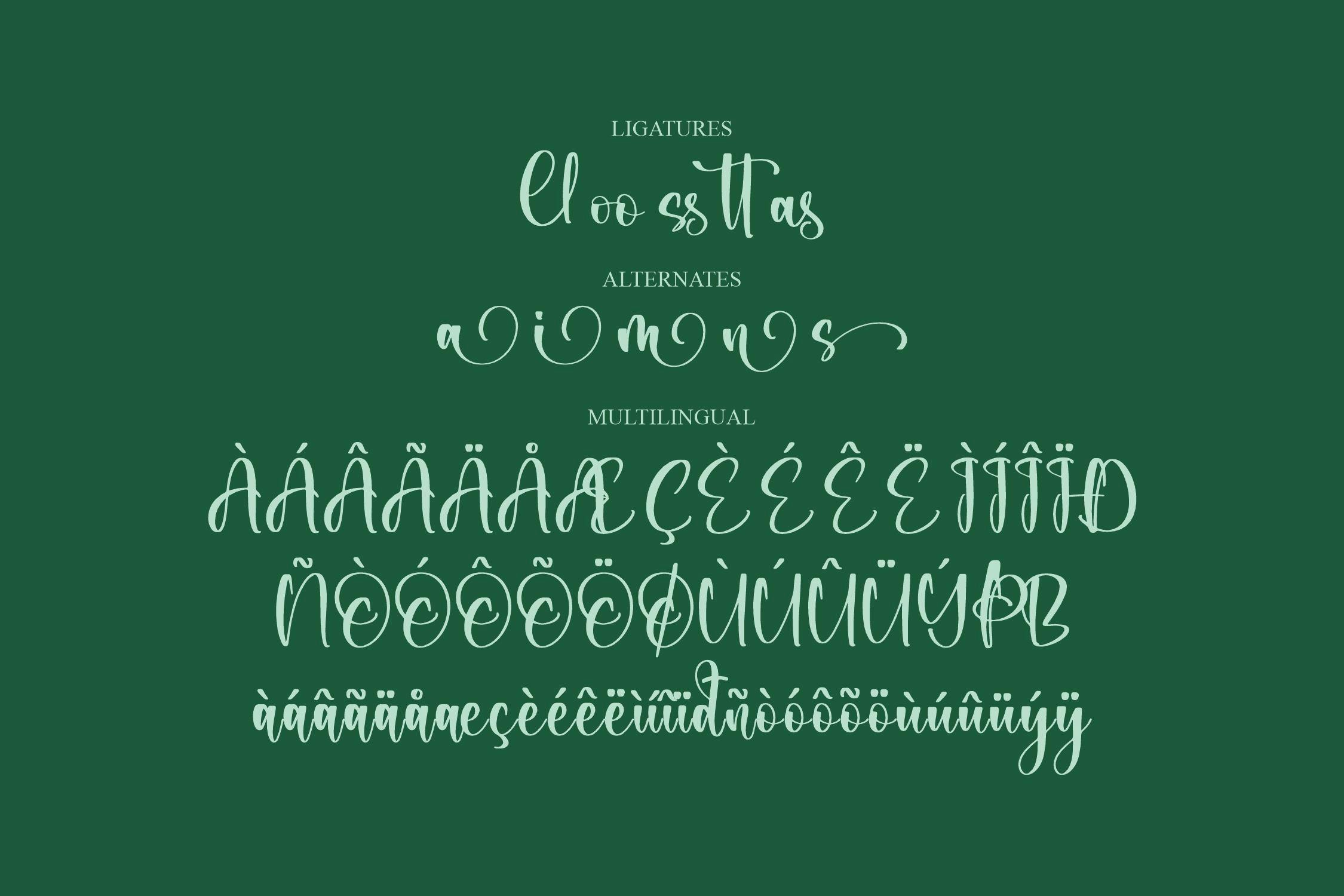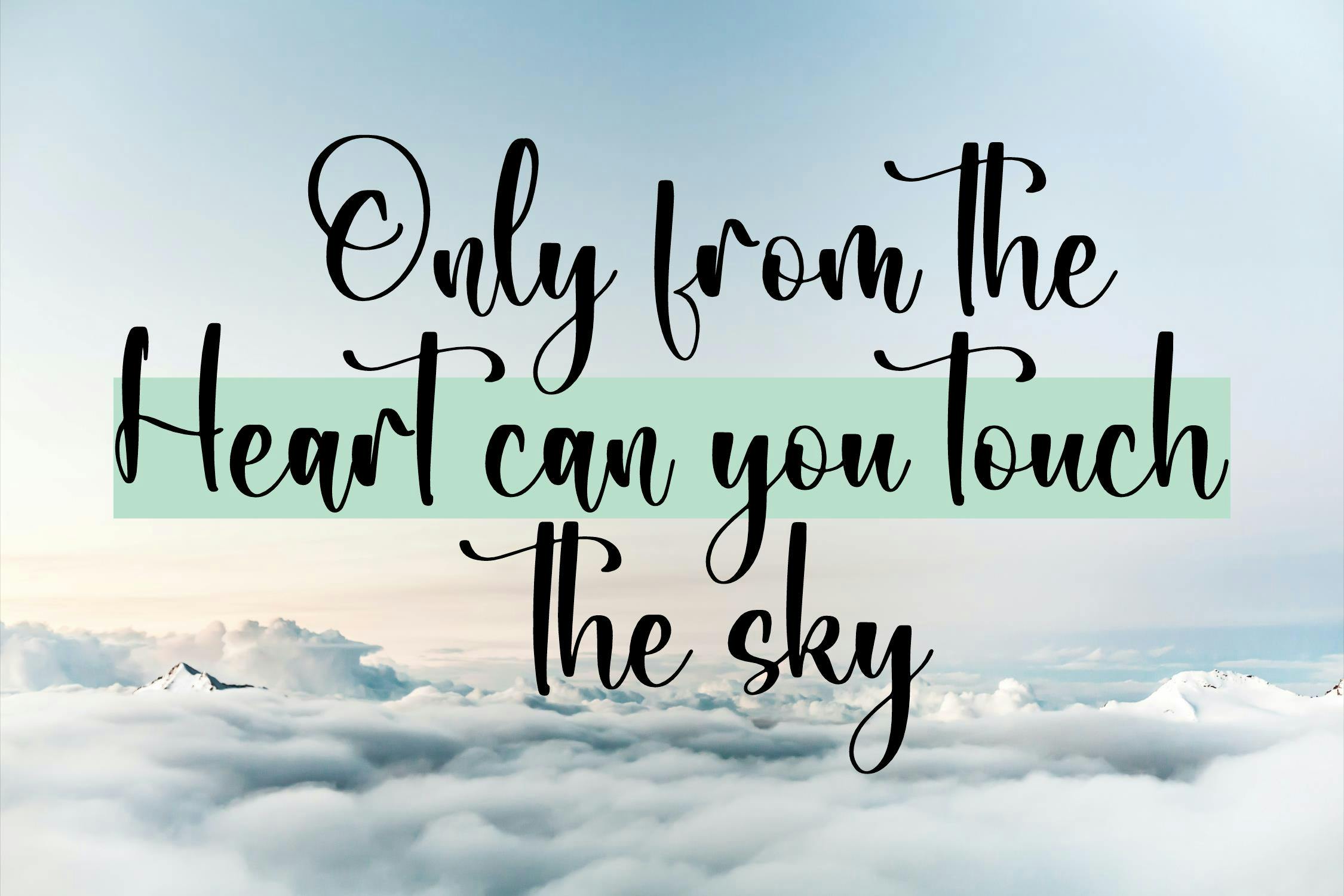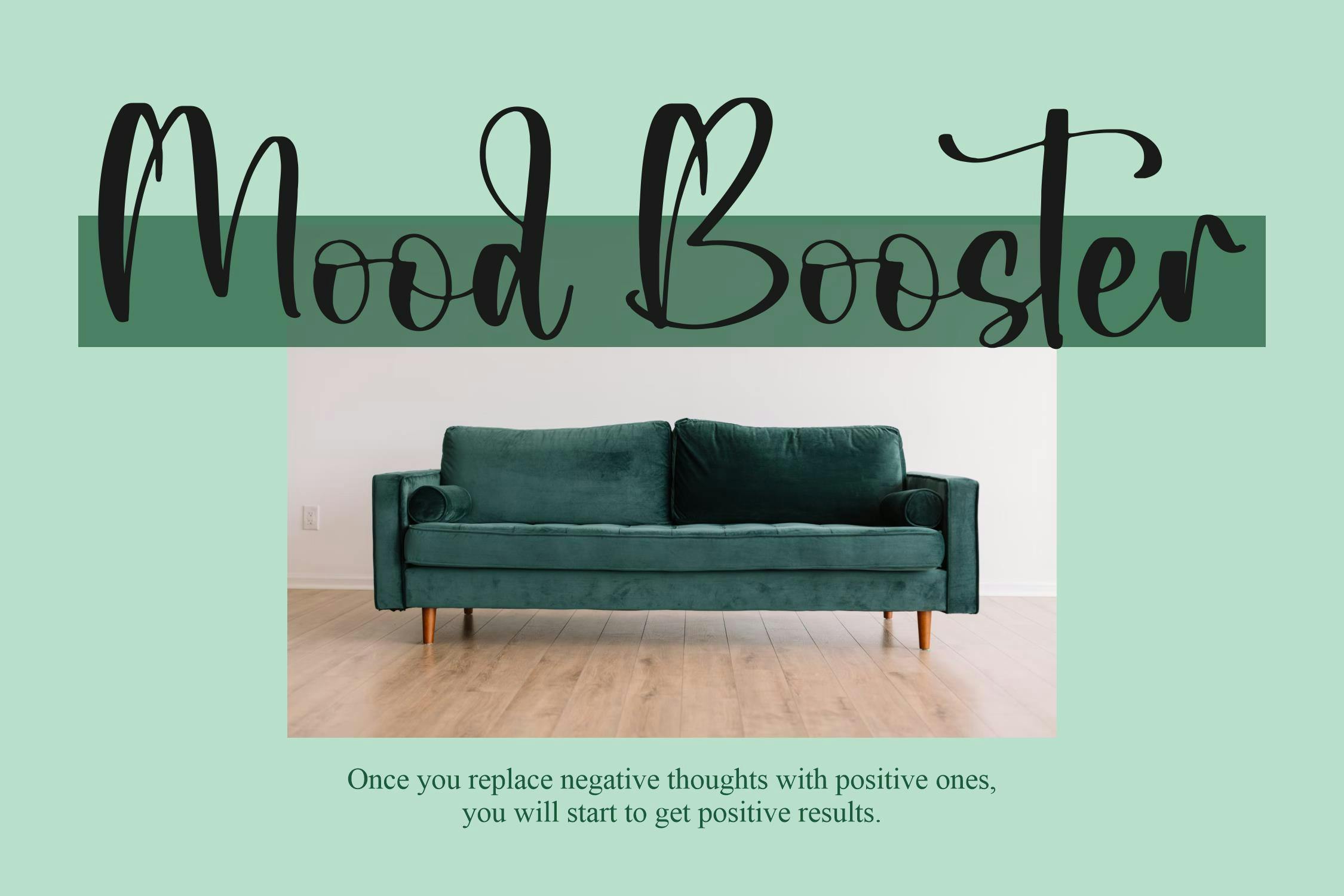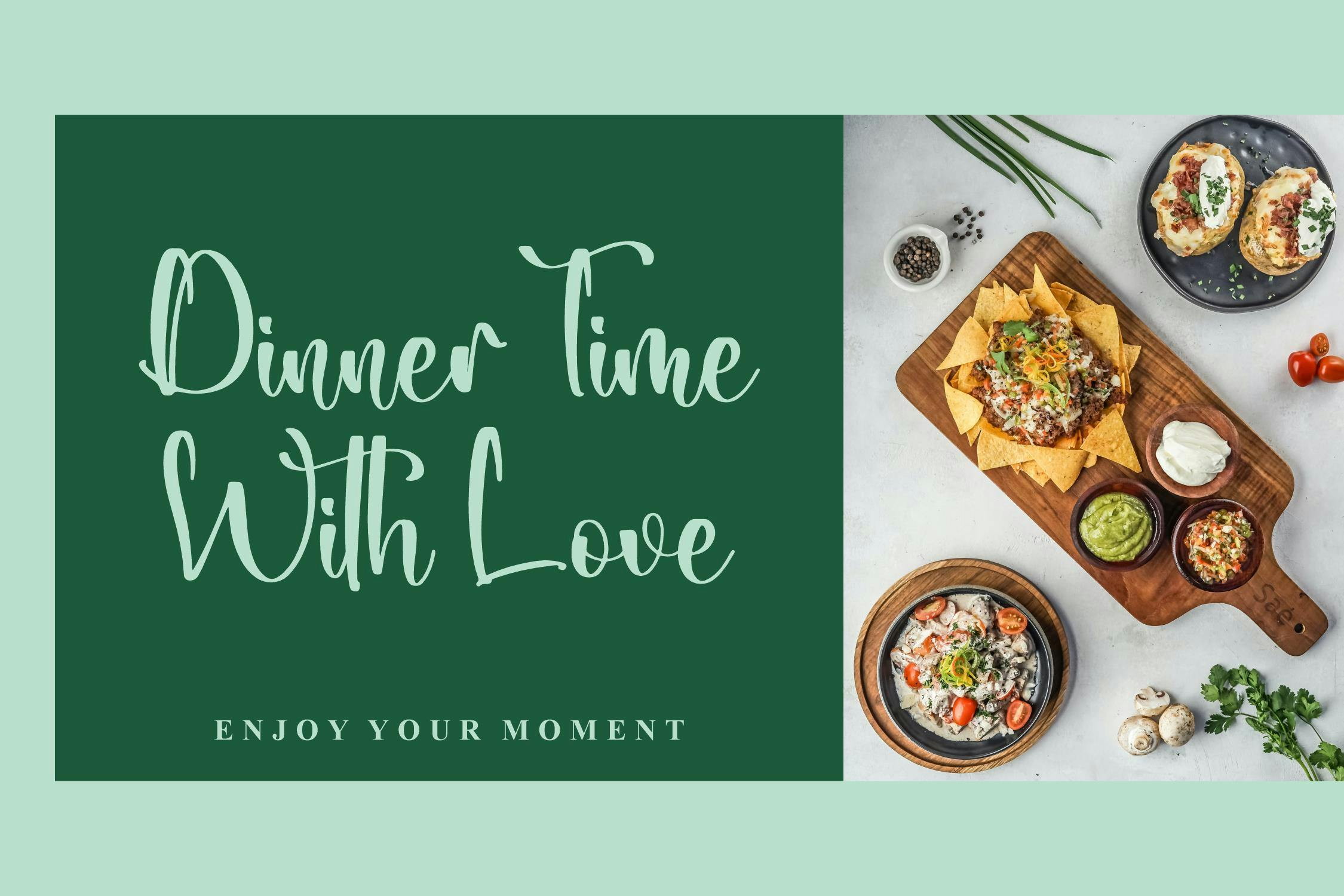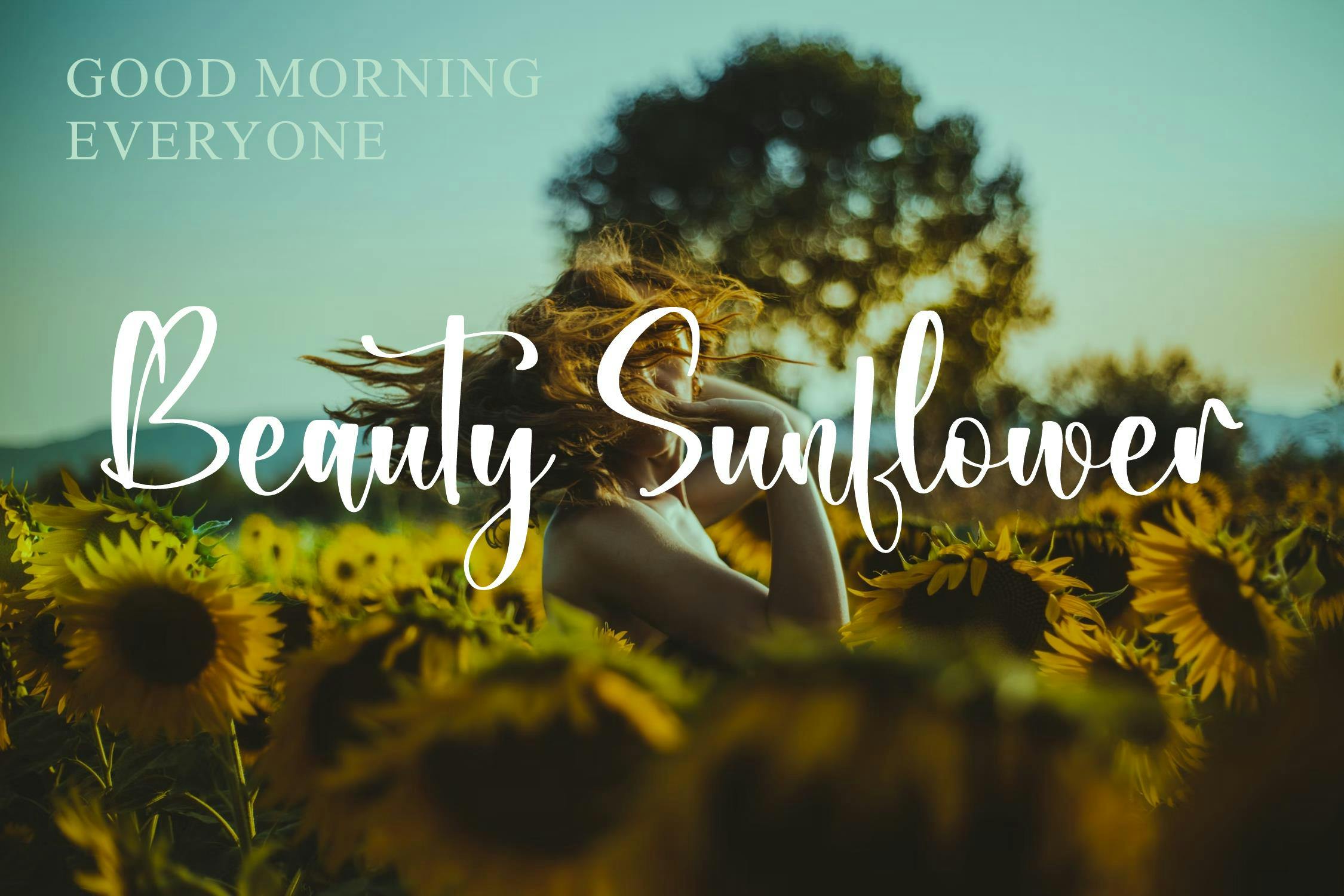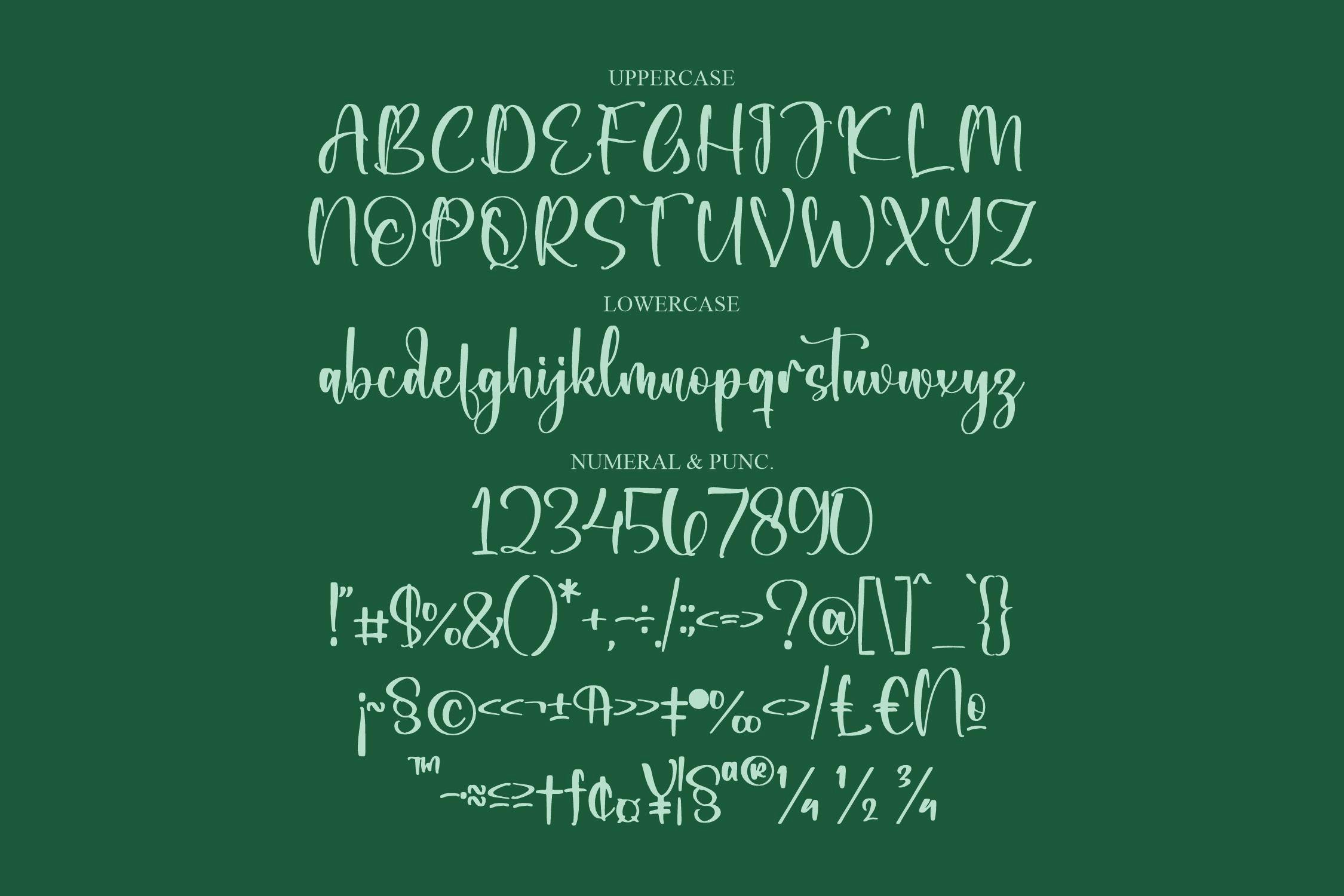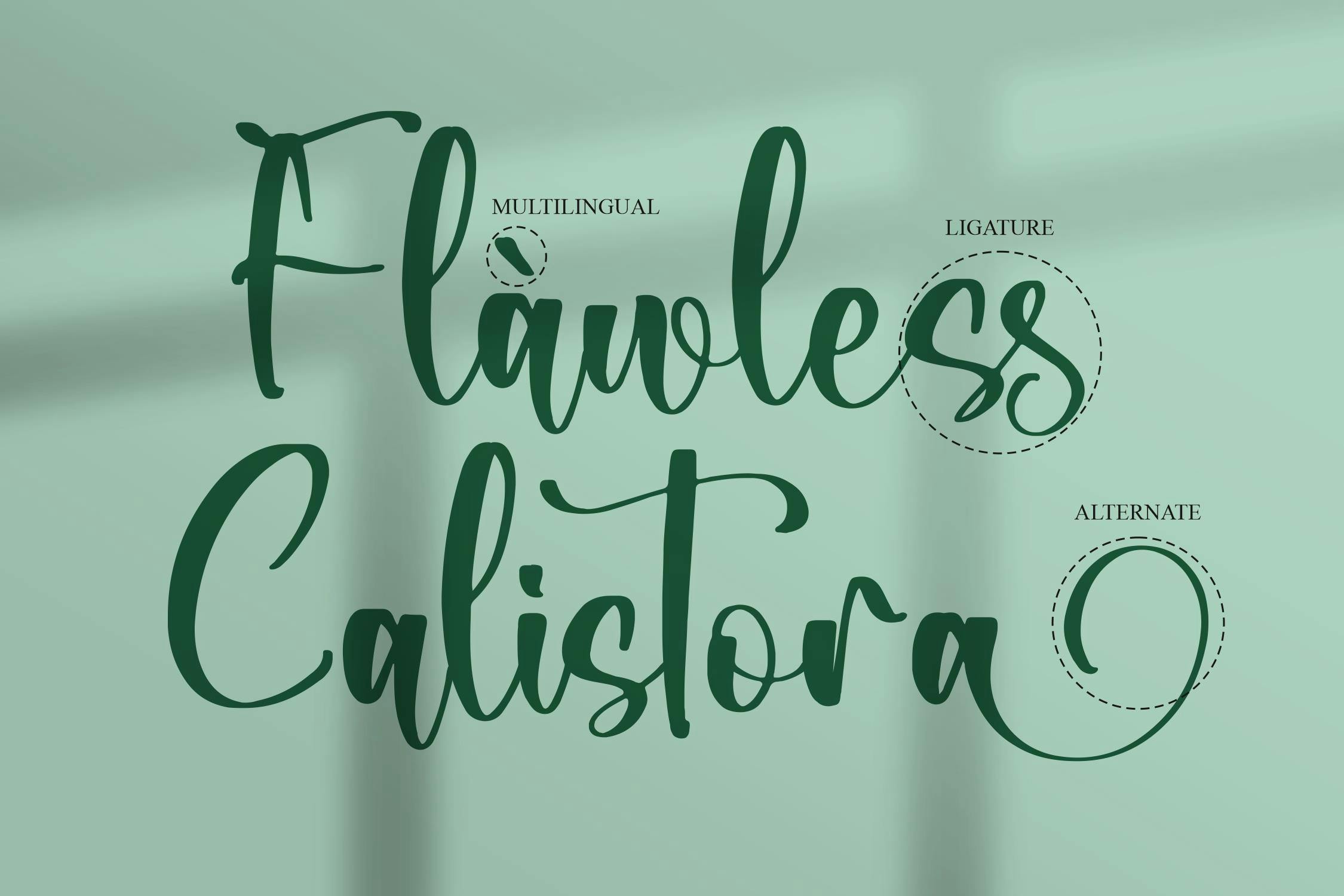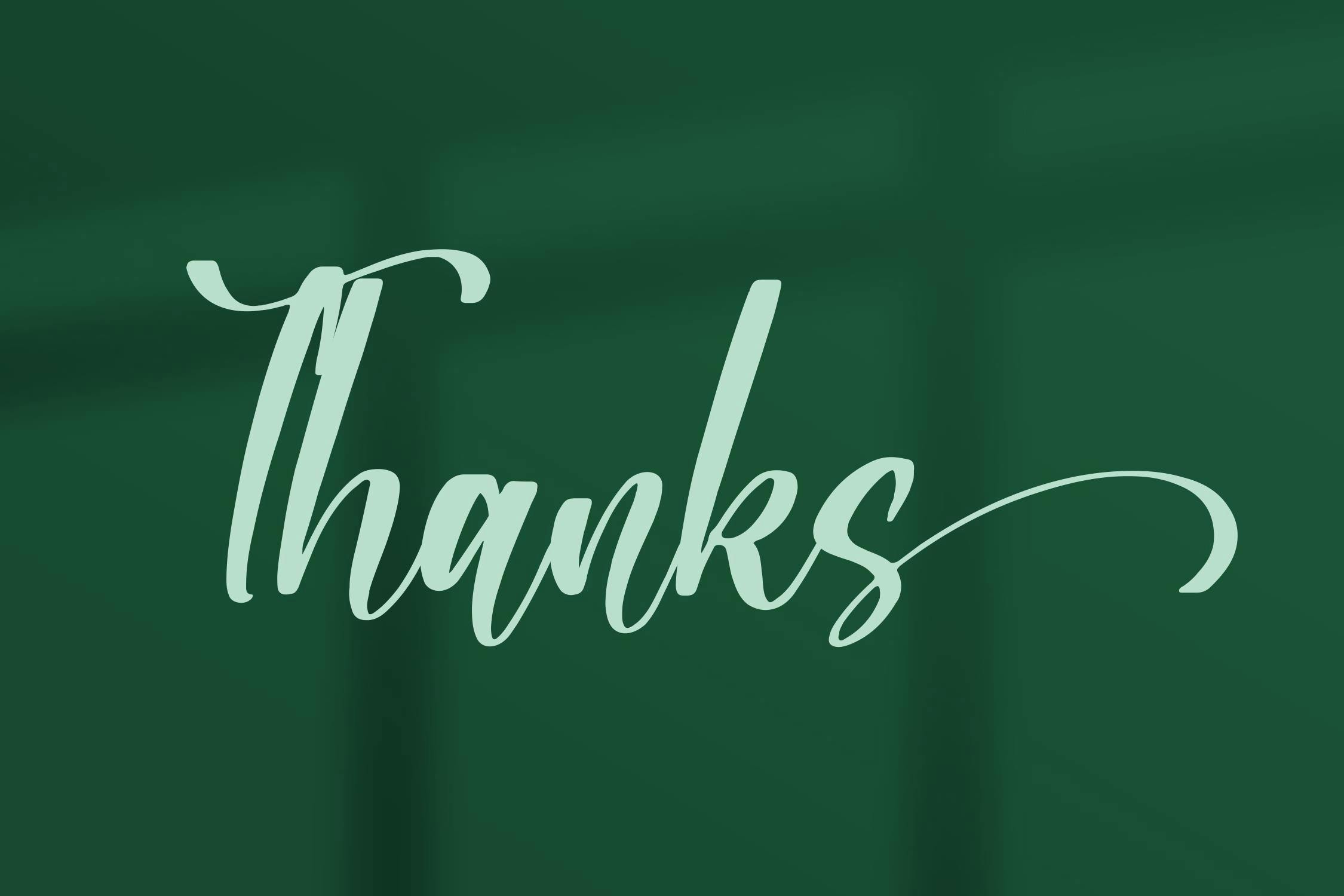
دانلود فونت Calistora مدرن و خلاقانه
Calistora Modern Script Font
فونت Calistora مناسب برای پروژه‌های دیجیتال و چاپی شما.
سلام آقایان و خانم‌ها، این فونت یکی از بهترین انتخاب‌ها برای تکمیل محصولات خلاقانه دیجیتال و چاپی شماست.
این فونت برای پوسترها، پست‌های شبکه‌های اجتماعی، برندینگ و پروژه‌های شخصی بسیار مناسب است.